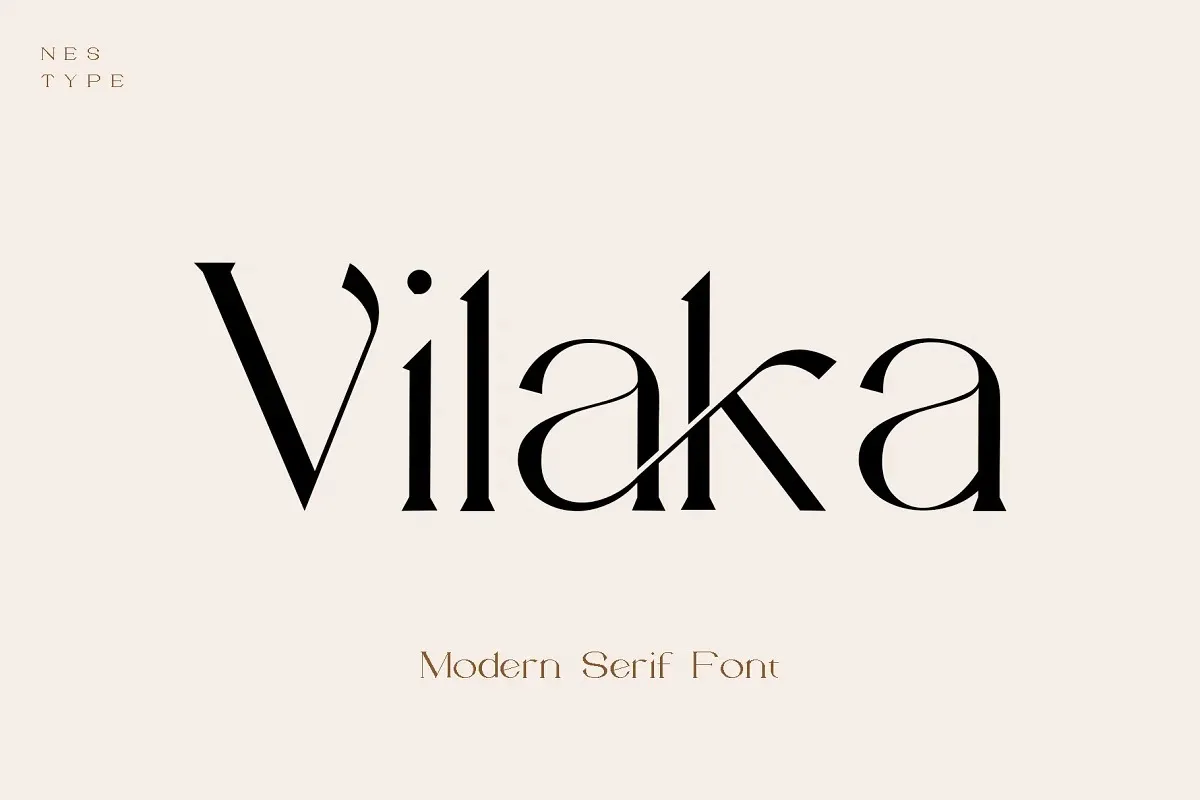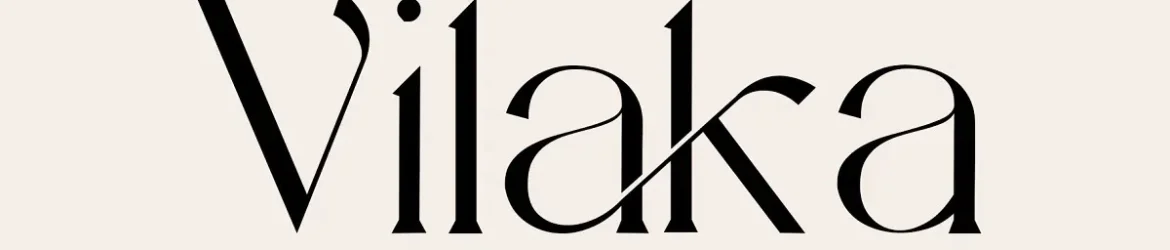
A Vilaka Font é uma elegante fóntica serifada criada pela Nestype com ligaturas incrivelmente bonitas. Composto por linhas altas e finas, esta fonte séria é perfeita para trabalhos editoriais. Suas ligaturas sutis dão ao texto um toque extra de sofisticação. E como uma fonte versátil, ela se adapta tanto em tamanhos pequenos quanto grandes. É ideal para projetos de logotipos, embalagens de produto, cabeçalhos de revistas e até mesmo como overlay estilizado sobre imagens de fundo. A Vilaka Font é uma opção perfeita para quem procura um texto moderno, mas ainda assim elegante, dando ao seu projeto aquele toque especial.